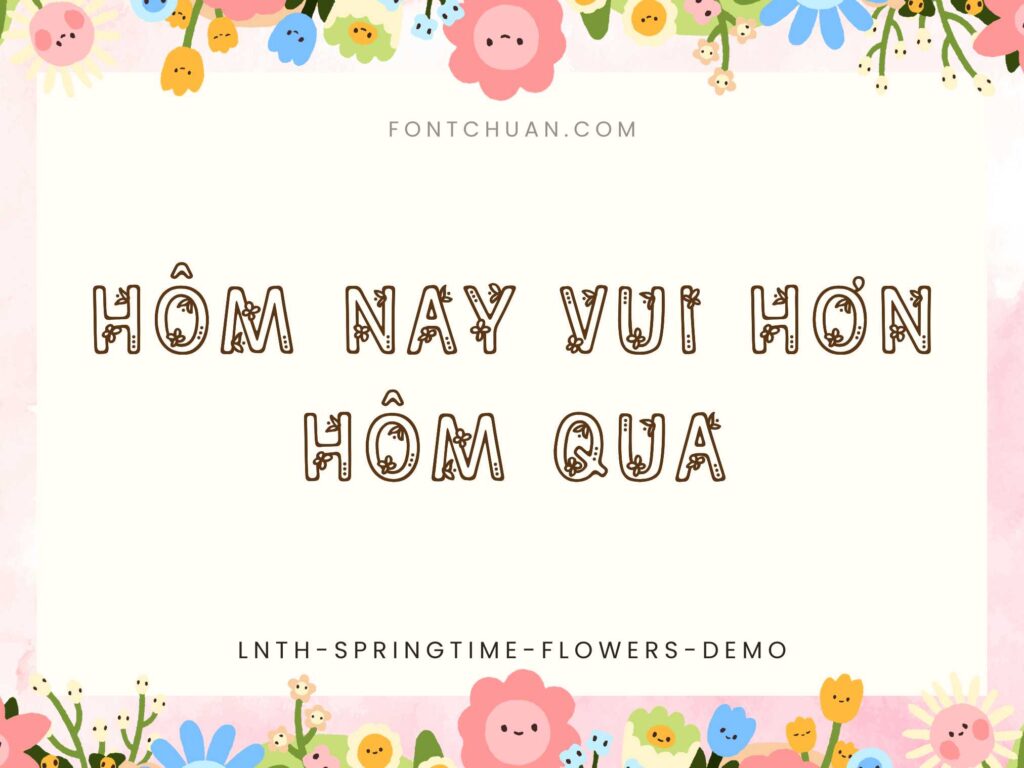
Font LNTH Springtime Flowers Việt Hóa
Font Springtime Flowers là một font chữ trang trí đầy sáng tạo, mang phong cách tươi sáng, nhẹ nhàng và lãng mạn. Với cảm hứng từ mùa xuân và hoa lá, font này được thiết kế với các đường nét mềm mại, uyển chuyển, mang đến cảm giác tự nhiên và tươi mới. Đây là lựa chọn hoàn hảo cho các thiết kế chủ đề lễ hội, thời trang, hoặc các dự án sáng tạo có yếu tố nghệ thuật
Phiên bản này đã được Việt hóa bởi LNTH, hỗ trợ đầy đủ tiếng Việt cùng hơn 50 ngôn ngữ khác, giúp người dùng dễ dàng ứng dụng trong thiết kế quốc tế. Font Springtime Flowers được các thành viên Font Chuẩn sưu tầm và đăng tải nhằm cung cấp một phong cách chữ trang trí độc đáo, thích hợp cho những ai yêu thích sự bay bổng và nữ tính
Về đặc điểm thiết kế, Springtime Flowers có các đường nét cong nhẹ nhàng, tạo cảm giác mềm mại nhưng vẫn rõ ràng. Kiểu chữ này rất thích hợp để sử dụng trong thiết kế thiệp mời, tiêu đề, bao bì sản phẩm hoặc các nội dung mang tính nghệ thuật
Font Springtime Flowers được ứng dụng rộng rãi trong các sự kiện như lễ hội, thiết kế mang phong cách mùa xuân. Nó phù hợp với nhiều ngành nghề như quảng cáo, spa, ẩm thực, bất động sản